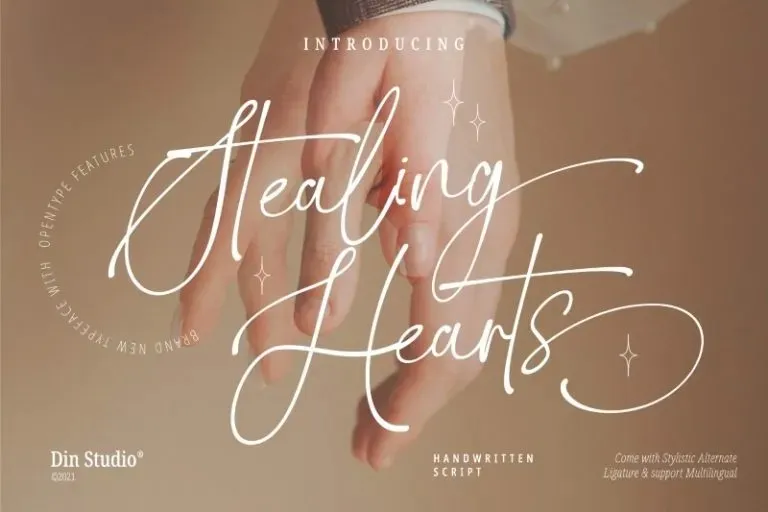
Stealing Hearts Font – Download Grátis
A Stealing Hearts Font é uma elegante tipografia feita à mão com um estilo moderno, perfeita para quem busca trazer a delicadeza do autógrafo à suas criações digitais. Esta fonte é ideal para criar cabeçalhos impressionantes, convites de aniversário e ocasiões especiais, logotipos memoráveis, ou até mesmo gráficos para redes sociais com uma personalidade única. Com seu estilo capturado em cada detalhe – desde as curvas suaves até os desenhos delicados dos tracinhos finos – a Stealing Hearts Font promete entusiasmar o público com um toque de encanto e elegância, garantindo que seus projetos se destacam. Ideal para designers que querem levar seu trabalho ao próximo nível, esta fonte é uma escolha inteligente para aqueles que desejam fazer suas ideias soar ainda mais impactantes.